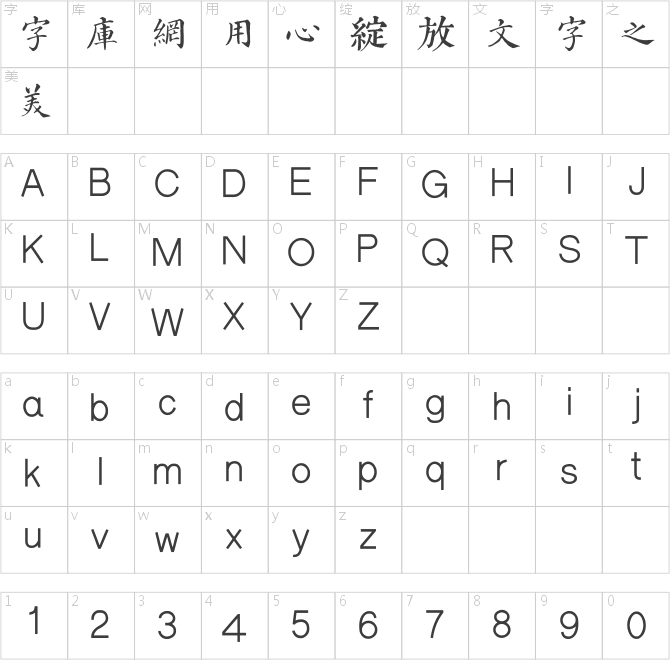
字體名稱: 邯鄲梁國治千字
邯鄲梁國治千字文字體下載邯鄲(清)梁國治千字文
乾隆十三年(1748)進士,殿試頭名狀元。由修撰累官東閣大學士兼戶部尚書。以經術勤吏治,清儉自守,好學愛才,治事敬慎縝密。有《敬思堂文集》。曾充任《四庫全書》副總裁。卒謚文定。
邯鄲梁國治千字文字體邯鄲(清)梁國治千字文字庫是一款讓人賞心悅目、百看不厭的中文字體,適合各類廣告和產品包裝設計應用,字體大小6.65MB,格式為ttf字體,上傳用戶是邯鄲字庫,作者/版權方為韓紹杰